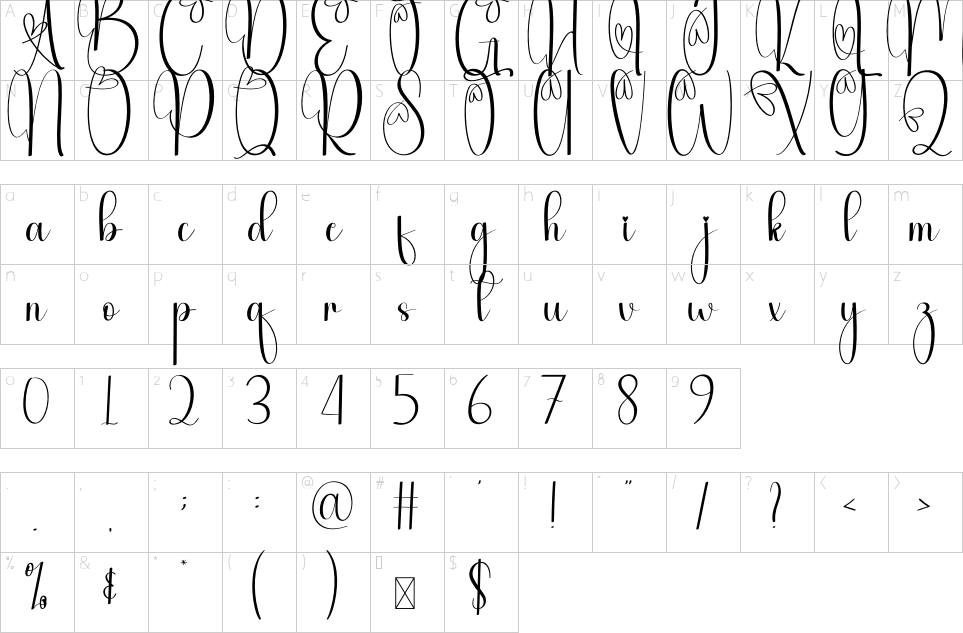
Descubra a delicadeza e a simplicidade da Angelina font, uma opção de fontes gratuitas perfeita para criar designs únicos e autênticos. Desenhada pelo designer desconhecido, esta fonte vem em versões para Windows e Mac, permitindo que você personalize seu design de maneira única. Com uma elegância discreta, Angelina oferece uma fonte que transmite confiabilidade e simplicidade, ideal para gráficos e designs de logotipo. Com seu design cuidadosamente criado por William Jhordy, a fonte Angelina se destacou entre os usuários, tendo sido baixada 971 vezes, demonstrando a sua popularidade e qualidade. Engaje seu público com a personalização única e alegre desta fonte, disponível de graça para todos os projetos digitais.